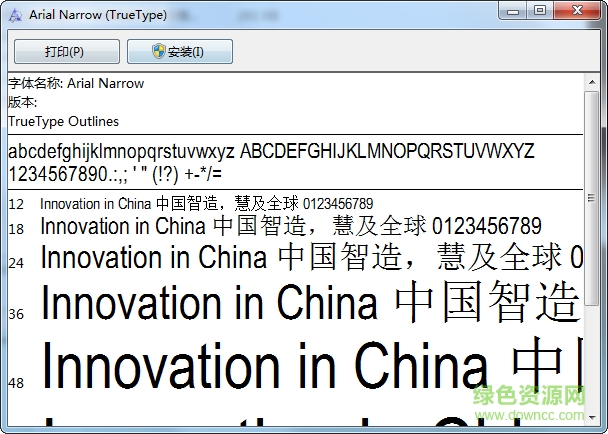
arial narrow regular字體是arial字體的細瘦變體,該字體線條流暢,表現(xiàn)力強,適合用于打印機、網(wǎng)頁設計等領域,需要更多無襯線體的小伙伴快來下載吧!
Arial作為 Monotype著名字體系列 Grotesque 的一個改編,其比例、字距、行距和比重都依照了 helvetica 的設計。因此盡管兩者筆畫上有細微的差距,但 Arial 還是能在非 PostScript 的排版場合替代 Helvetica,并且兩者在很小的尺寸下很難區(qū)分。